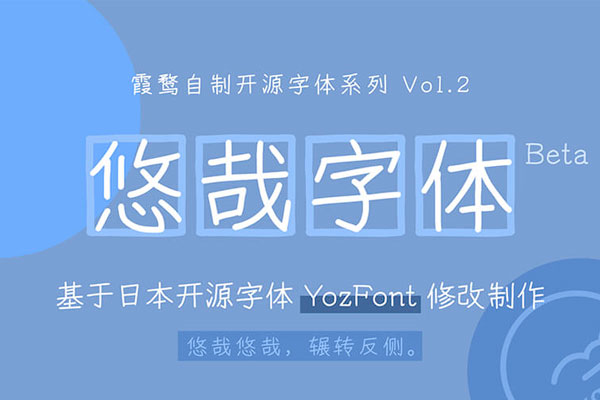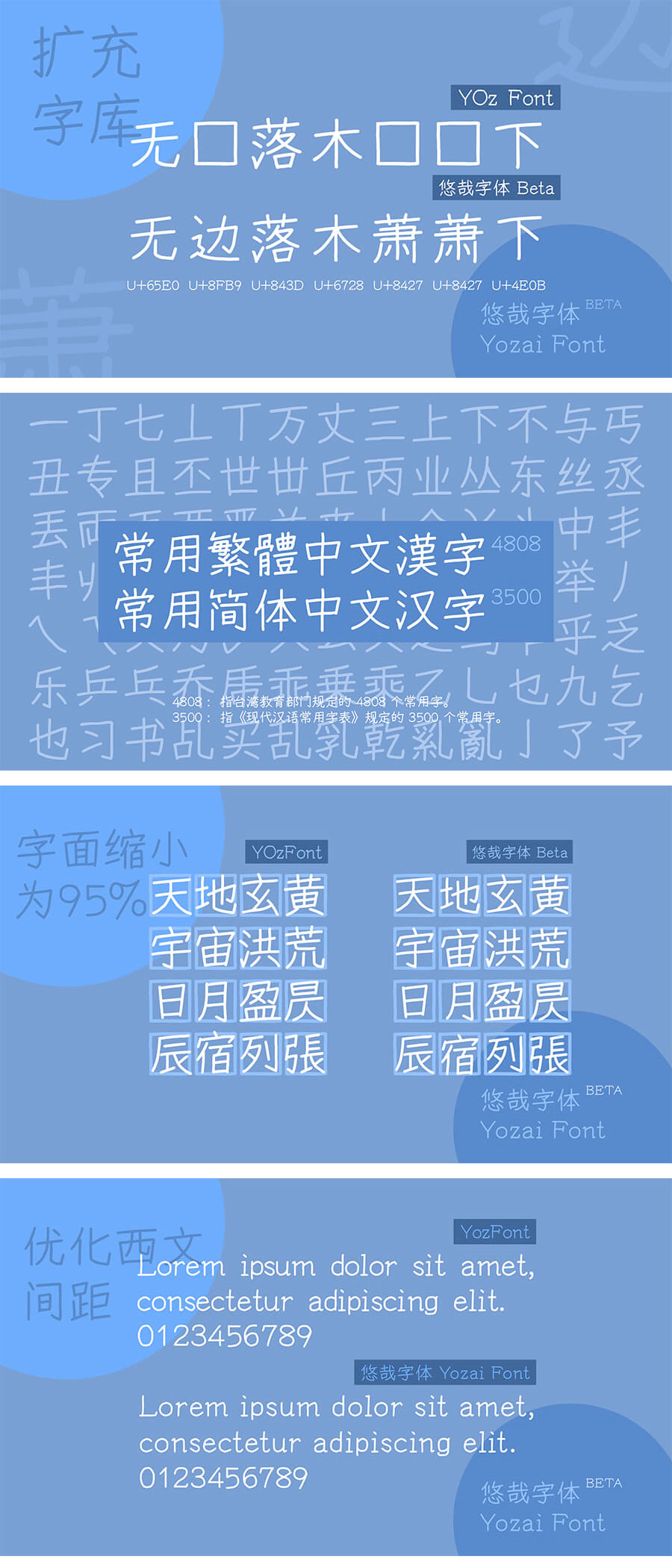
悠哉字体
悠哉字体(Yozai Font)是一款由中国大陆的字体设计师落霞孤鹜基于免费开源的日本Y.OzFont改造的手写风格字体。该字体已经在原版字体的基础上,补全了对应的繁体字的简体字,以及4808个常用繁体中文汉字和3500个常用简体中文汉字。
这些汉字包括台湾教育部规定的4808个常用汉字和《现代汉语常用字表》规定的3500个常用汉字。在优化方面,悠哉字体缩小了字面至原来的95%,并对西文和标点符号的显示进行了优化。
需要说明的是,该字体目前仍处于测试版阶段。尽管已经做了很多补全和优化工作,但仍有部分汉字保持了日本写法。未来的更新计划包括补全GB2312范围内的所有汉字,并将GB2312内汉字的写法调整为中国内地的字形。由于发布者并非专业设计师,字体可能不那么美观,部分汉字可能看起来有些奇怪,同时补进去的字和原版字体可能略有违和感。
2021-07-19悠哉字体更新到v0.85版本,扩展了字重,现在已有4个字重。
悠哉字体效果预览
悠哉字体字体效果预览